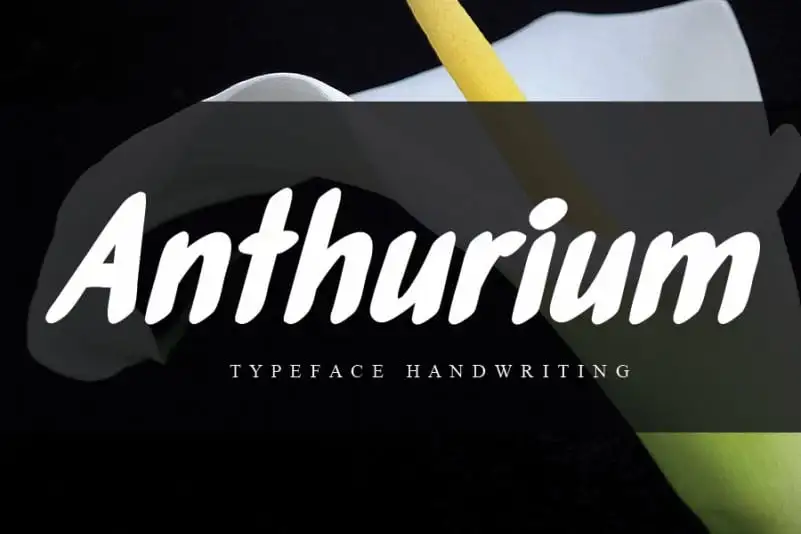
Anthurium Brush Font – Download Grátis
Anthurium Brush Font é uma tipografia escrita à mão que transmite alegria e amabilidade. Sua natureza única e singular torna-a perfeita para uma ampla variedade de projetos gráficos. As linhas espessas e os detalhes delicados da fonte criam um contraste que dá a ela um toque especial. Ela é perfeitamente adequada tanto para textos leves quanto para se destacar em design gráfico, criando uma sensação de conforto e suavidade ao mesmo tempo em que exibe uma elegância rica e autêntica. E o melhor: a única limitação são seus próprios sonhos! Esse é um recurso de fontes que certamente se tornará seu parceiro perfeito para todos os tipos de projetos criativos. Este Anthurium Brush Font pertence à categoria de fontes Script, cuidadosamente desenhada pelo designer eikastudio. É uma escolha ideal para designers gráficos em busca de um elemento único que pode enriquecer suas criações sem deixar de ser funcional.